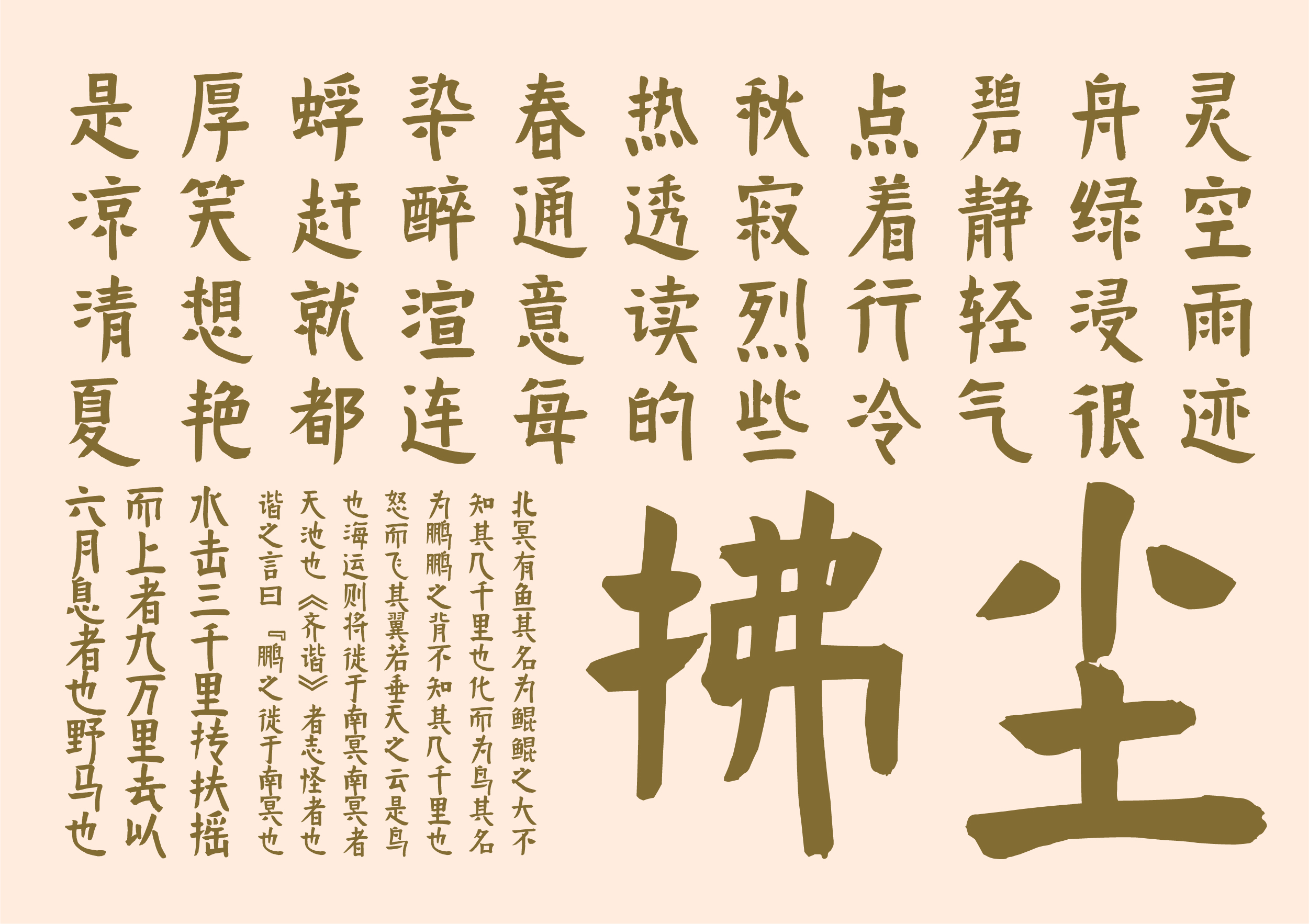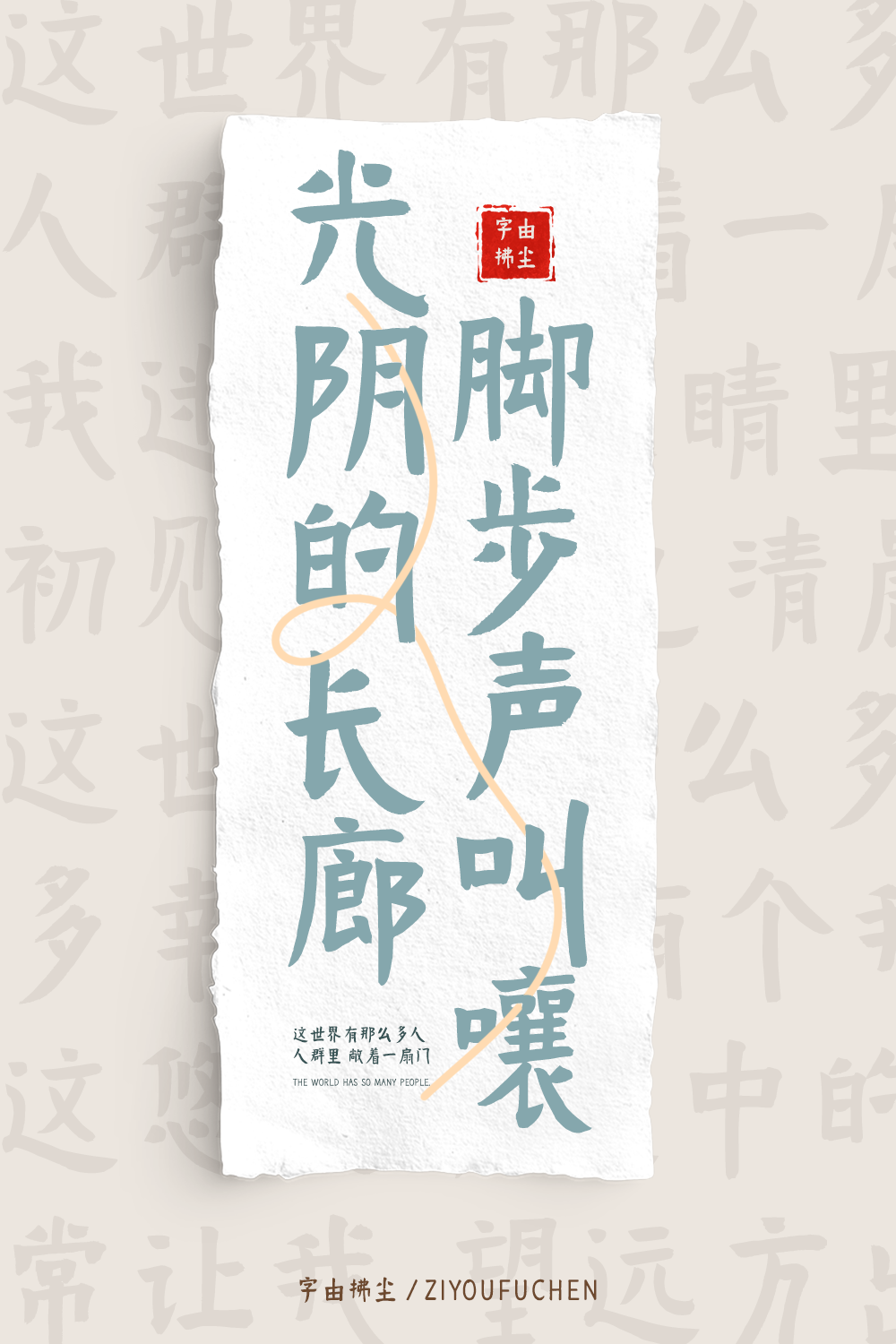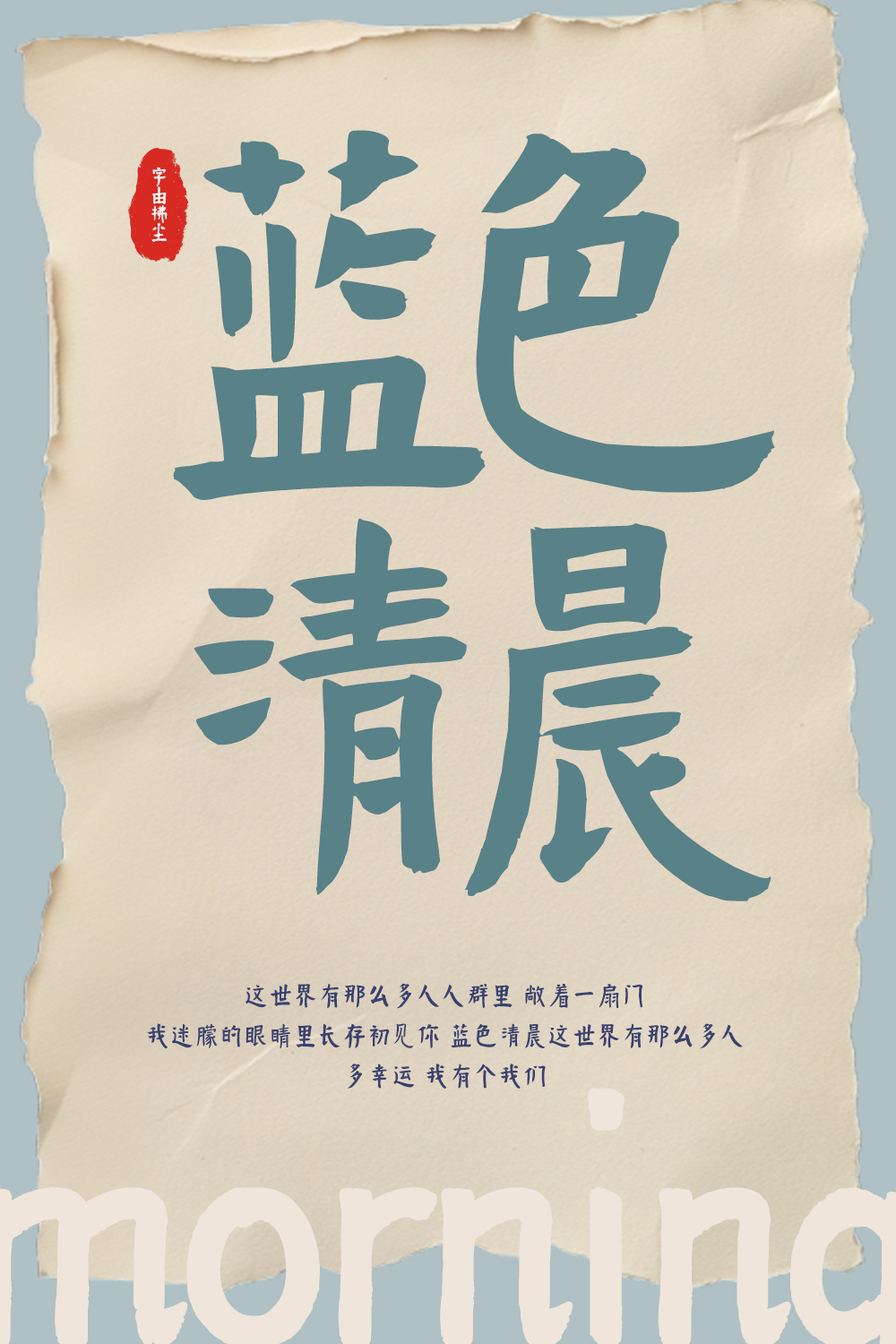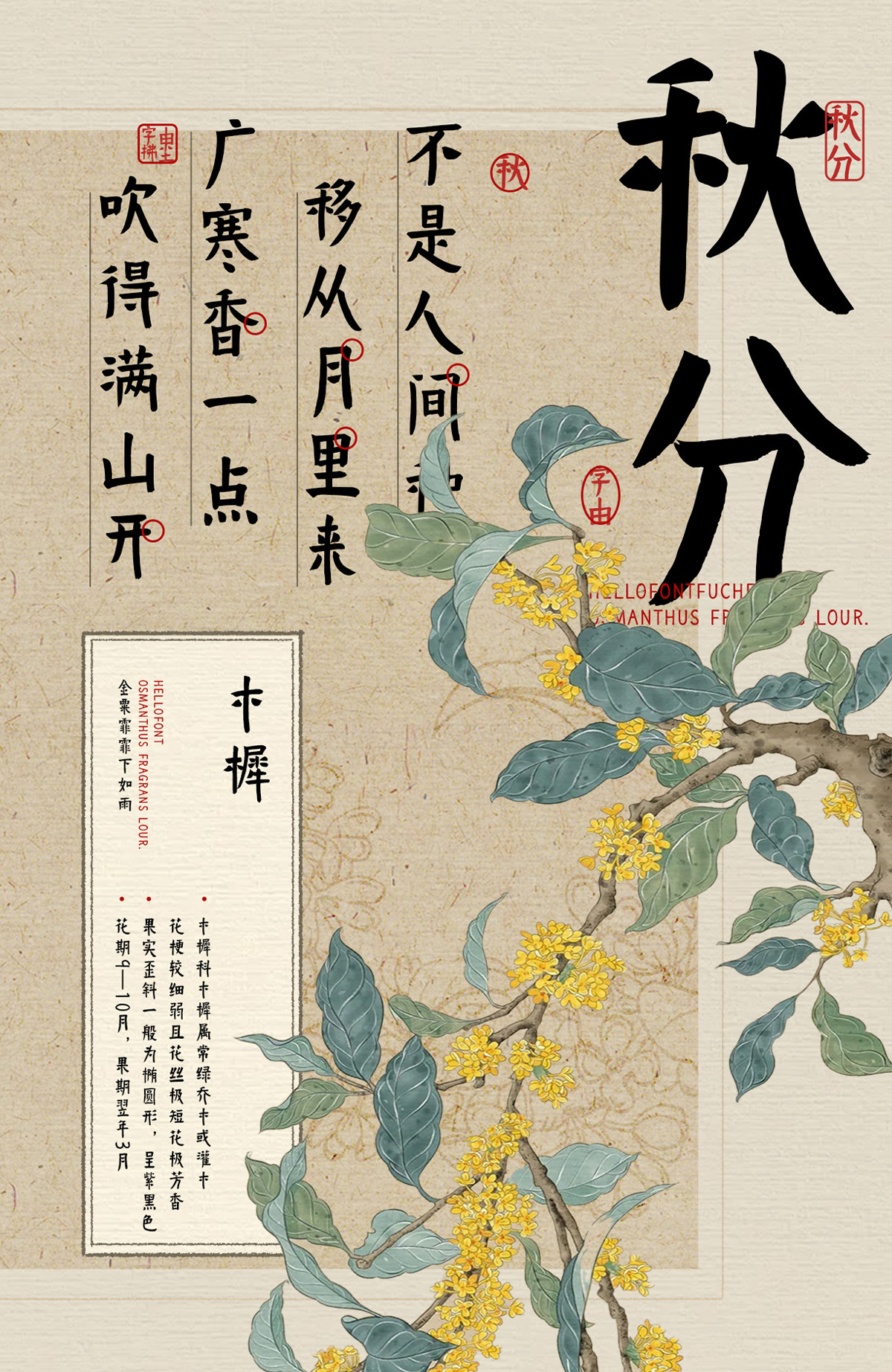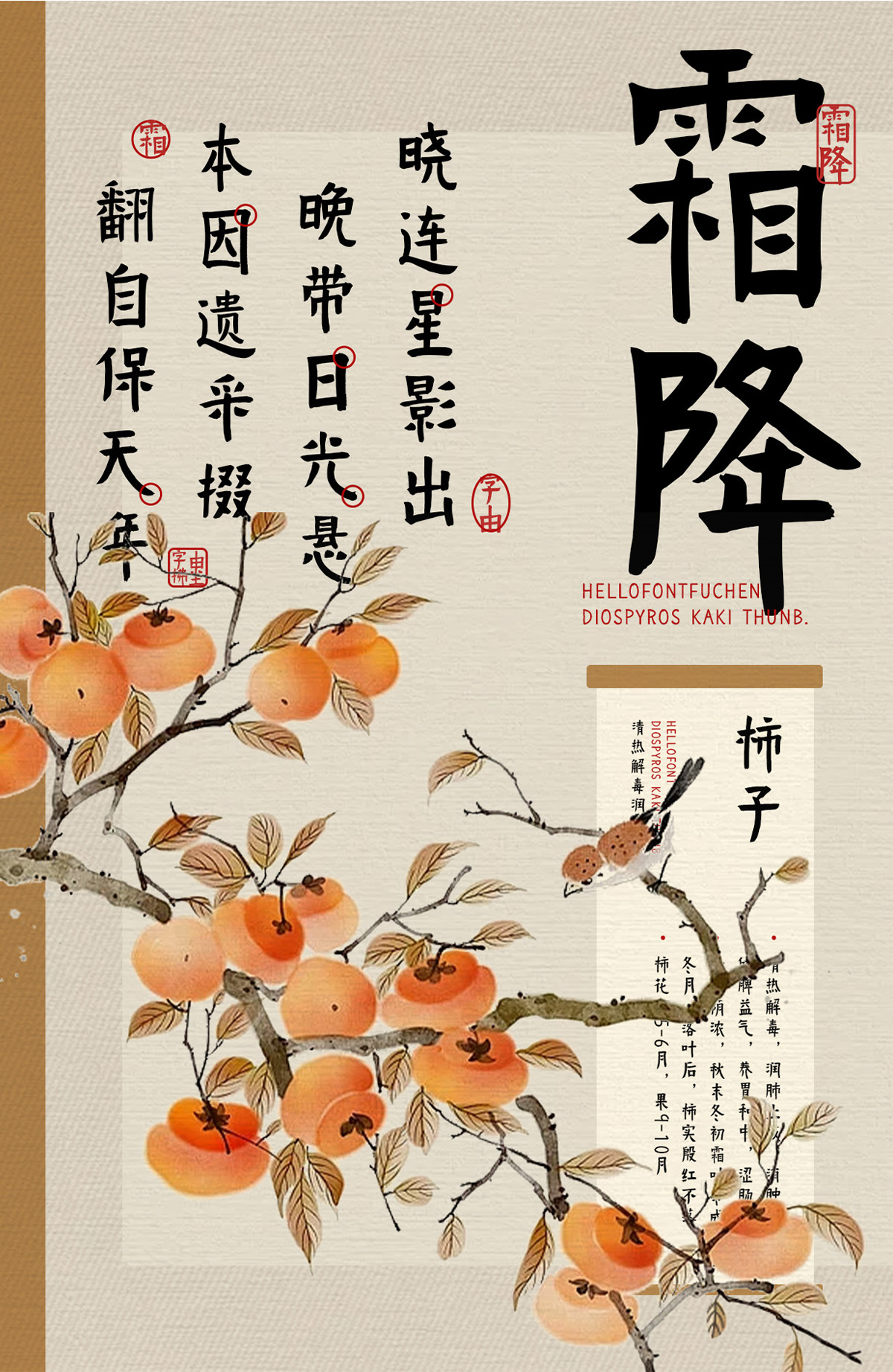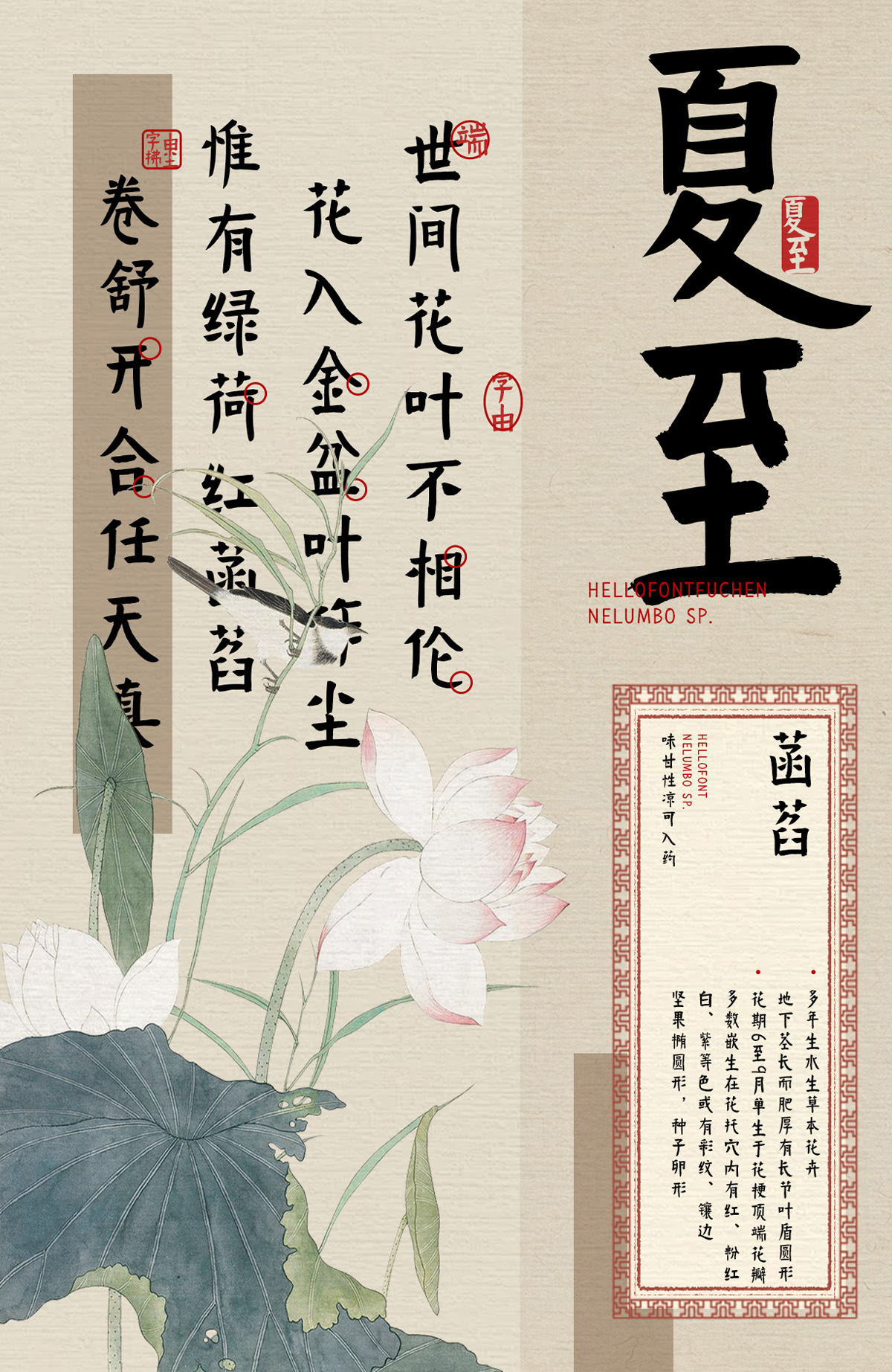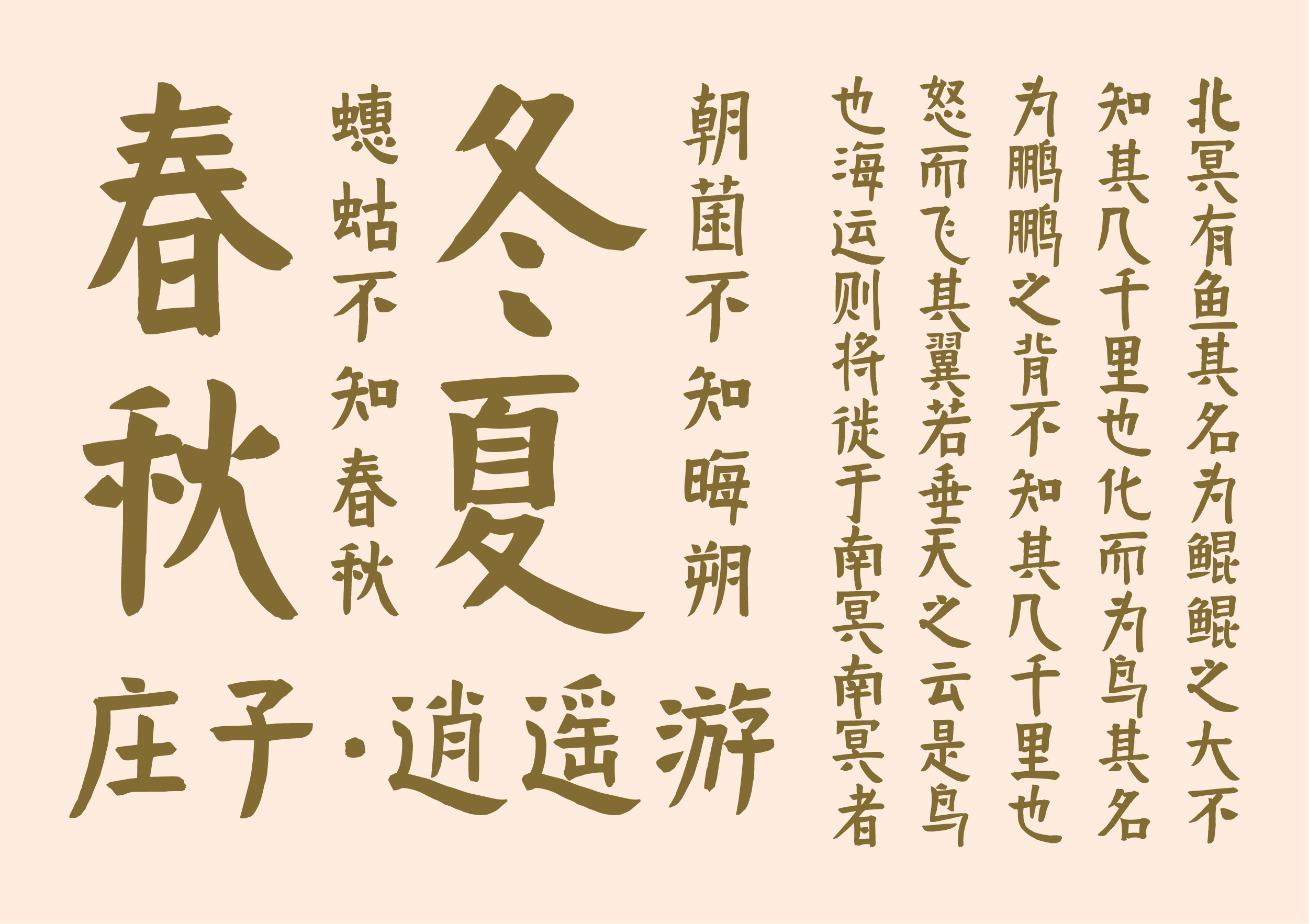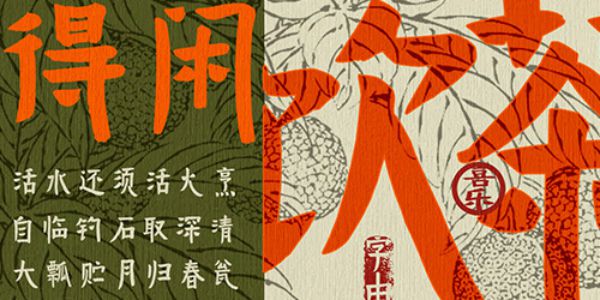
字由拂尘荣获2026亚洲设计奖银奖,演绎东方禅意美学
字由拂尘荣获亚洲设计奖银奖
不久前,亚洲设计奖组委会正式公布新一届获奖名单。字由参赛作品,字体“字由拂尘”荣获“Graphic Design - Publication ASIAN Design Awards 2026”银奖。这是字由在2026年获得的首个专业设计奖项。
字由拂尘字体设计理念
“字由拂尘”以禅意为设计内核,通过重心上移、中宫收紧的结构处理,营造出飘逸轻盈的视觉感受。笔划设计在安定中蕴藏动态,撇、捺与钩画融入自然提按,犹如拂尘划过空气般流畅舒展。
字体还巧妙融入篆书与金文笔意,在保持高辨识度的同时,增添古朴雅致的文化韵味。其独特风格尤其契合茶饮、养生、非遗技艺、古籍文创等富含文化底蕴的应用场景。
字由在多项国际设计赛事获得荣誉
回顾2025年,字由的多款原创字体屡获国际认可,“点字爨宝子”获加拿大未来设计奖金奖,“点字清逸隶”获伦敦设计奖银奖,“字由拂尘”亦曾摘得法国设计奖银奖。
国际设计赛事赋予的荣誉,不仅代表着专业能力的肯定,也是字由将中国书法韵味、汉字字体带去国际舞台的积极反馈。
未来,字由将继续致力于融合传统文化与现代设计,为各位设计师带来兼具美学价值实用性的优质字体,让用字更自由!